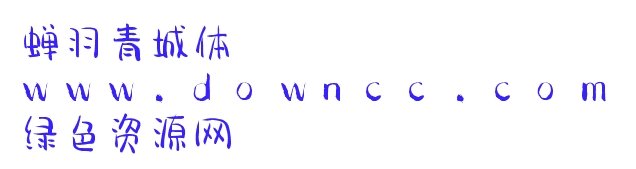
蟬羽青城體是蟬羽系列的第二款字體,延續(xù)了軟頭毛筆的手寫(xiě)字體風(fēng)格,給人更加文藝清晰的視覺(jué)體驗(yàn),英文是用來(lái)圓角格式,更加突出,喜歡的朋友就來(lái)綠色資源網(wǎng)試試吧!
該字體是用軟頭筆書(shū)寫(xiě),字體風(fēng)格秀氣、活潑可愛(ài)、新穎、個(gè)性、小清新、時(shí)尚、有趣,適用于視頻、 書(shū)籍、 游戲 、 動(dòng)漫、影視 、 屏顯等方面。特別適合年輕的萌妹子和萌漢子。
蟬羽青城體,輕如蟬羽娟美若青城,是一款極具卡通字體風(fēng)格和藝術(shù)字體特色的個(gè)性字體,給你清爽干凈的藝術(shù)效果,可以使用在平面設(shè)計(jì)、海報(bào)設(shè)計(jì)等各個(gè)領(lǐng)域!